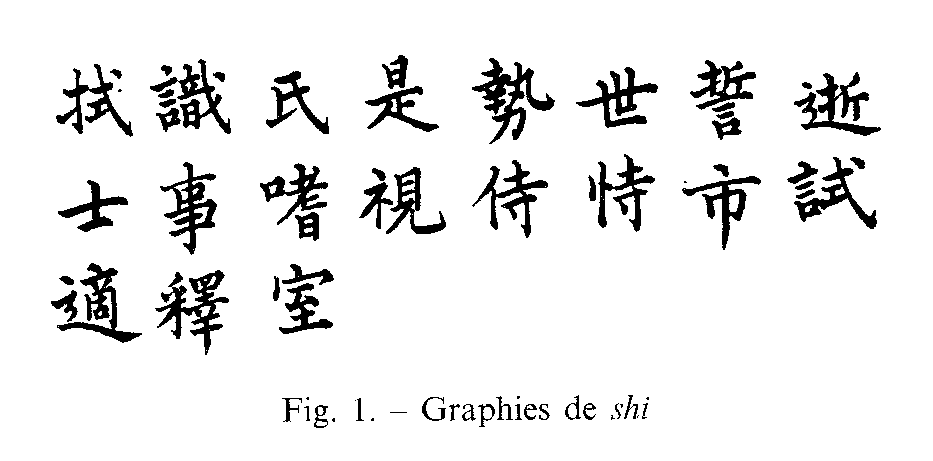
Qui vous parle d'"ambiguïté" ?
Vous semblez confondre deux choses : que l'élément phonétique d'un caractère soit (en général) une (assez) bonne indication de la prononciation (si on connaît la prononciation de cet élément quand il apparaît seul,, comme caractère à part entière), et le fait que la même prononciation pourra s'indiquer par des éléments phonétiques différents.
Les chiffres sont très clairs, en effet : de 858 à 1 358 éléments phonétiques distincts, alors qu'il n'y a que 206 rimes distinctes, pour les 1 382 syllabes possibles. Autrement dit, vous n'aurez aucun mal, en sélectionnant une syllabe donnée, affectée d'un ton donné, à trouver (en moyenne) sept (7) éléments phonétiques différents dans des caractères signifiant des mots distincts, tous se lisant de la sorte - et en plus (statistiquement) au moins une forme sans élément phonétique... Mais ça ne change rien à la nature phonétique de l'immense majorité de ces caractères !
Mais on comprend que la structure la plus générale du caractère chinois, faisant apparaître un élément sémantique (le plus souvent : le déterminant, ou clé) et un élément phonétique (ce qu'*aucun* sinologue ne songerait à contester...) a puissamment aidé a développer l'analyse "fanqie" de ces caractères, utilisée pendant 10 siècles par les dictionnaires des rimes - y compris pour les 3 % ne présentant pas une telle structure.
Le problème majeur de cette méthode, bien entendue, est qu'elle est intimement liée au seul mandarin, plus précisément au dialecte de Pékin, dans sa forme "officielle" ("putonghua") - et, qui plus est, qu'elle est tributaire de l'évolution phonologique de la langue, imposant à la longue des redistributions et reclassifications des caractères.
C'est ce type de considérations qui a amené, par la suite, un regain de faveur du système des clés, qui a l'avantage - tout en restant fort abstrait (ce qui conduira à la diffusion du mythe d'une écriture conceptuelle, faites d'"idéogrammes") - de convenir à l'ensemble des langues chinoise (dans leurs divers dialectes), et même aux langues non chinoises adoptant ces caractères : coréen, japonais (kanji), vietnamien d'avant la conquête française... et, par surcrroît, d'être insensible aux inévitables mutations phonologiques.
Mais, à ce compte, si on n'est pas soi-même chinois, on perd vite de vue la construction fort simple, et systématique de ces caractères. C'est bien ce qui est arrivé, et que vous démontrez encore... puisque vous refusez de *voir* que plusieurs groupes de caractères, dans la liste que vous exhibez si triomphalement, comportent... les mêmes éléments.  (Entendons : autant de fois qu'il y a de groupe à distinguer...) Ce qui devrait vous amener à réviser une certitude, "étayée" à si bon compte...
Je vous demanderai instamment de comparer : le 1er et le 3e (à partir de la gauche) de la 1re rangée, et le dernier à droite de la 2e rangée ; le 4e et le 5e de la 2e rangée ; l'avant-dernier et le dernier de la 1re rangée.
Ce qui est moins évident, pour le néophyte, est que le 1er caractère de la 2e rangée est lui-même composé, et phonétique : "lettré", ici, doit se comprendre comme "personne sachant compter de 1 à 10" (sic) - le symbole "10" chinois étant une simple croix (cf. le X romain !), qui se lit "shi", affecté du deuxième ton. Le symbole pour 1, à sa base, est le trait horizontal simple, qui se lirait 'yi" affecté du 1er ton.
Oui : le décryptage n'est pas évident de prime abord, surtout en calligraphie moderne, comme ici... Mais enfin, le jugement des Chinois eux-mêmes, quant à la structure des caractères qu'ils utilisent (opinion admise depuis deux millénaires) - ce jugement devrait plutôt emporter votre adhésion, plutôt que suciter une tentative (nécessairement vaine, pour ne pas dire futile) de le contredire. Quitte à apprendre à lire ces petites bêtes (ce qui n'est pas évident, je vous l'accorde !).
Je vous propose (pour régler la question, de faire la recherche sur le site déjà indiqué de Zhongwen.com (Chinese Characters and Culture), qui est une ressource précieuse pour voir (et comprendre) comment ça marche :
http://zhongwen.com/
Sur la page d'accueil, à la rubrique "Search", cliquez sur "pronunciation", et entrez "shi" (sans indication de ton). Vous arrivez directement sur une page vous proposant les 408 syllabes du mandarin (en translittération pinyin), sans accent. Cliquez sur "shi".
Vous arrivez sur une page ou apparaissent, cette fois, toutes les formes monosyllabiques de "shi", affectées des divers accents (ou absence d'accent) possible, suivies des formes disyllabiques débutant par une de ces syllabes. Et, pour chaque entrée, les caractères afférents. Se rappeler que, à chaque étape *tout* caractère chinois apparaissant sur la page est cliquable, et vous livrera la même mine d'informations (et de renvois potentiels...).
En réalité, les caractères chinois ont tout à la fois une valeur phonétique et une valeur sémantique, absolument indissociables. En Chinois, apprendre à écrire, c'est apprendre le vocabulaire... Alors pourquoi restreindre l'utilité de 97% de ses signes à leur seule valeur phonétique ?